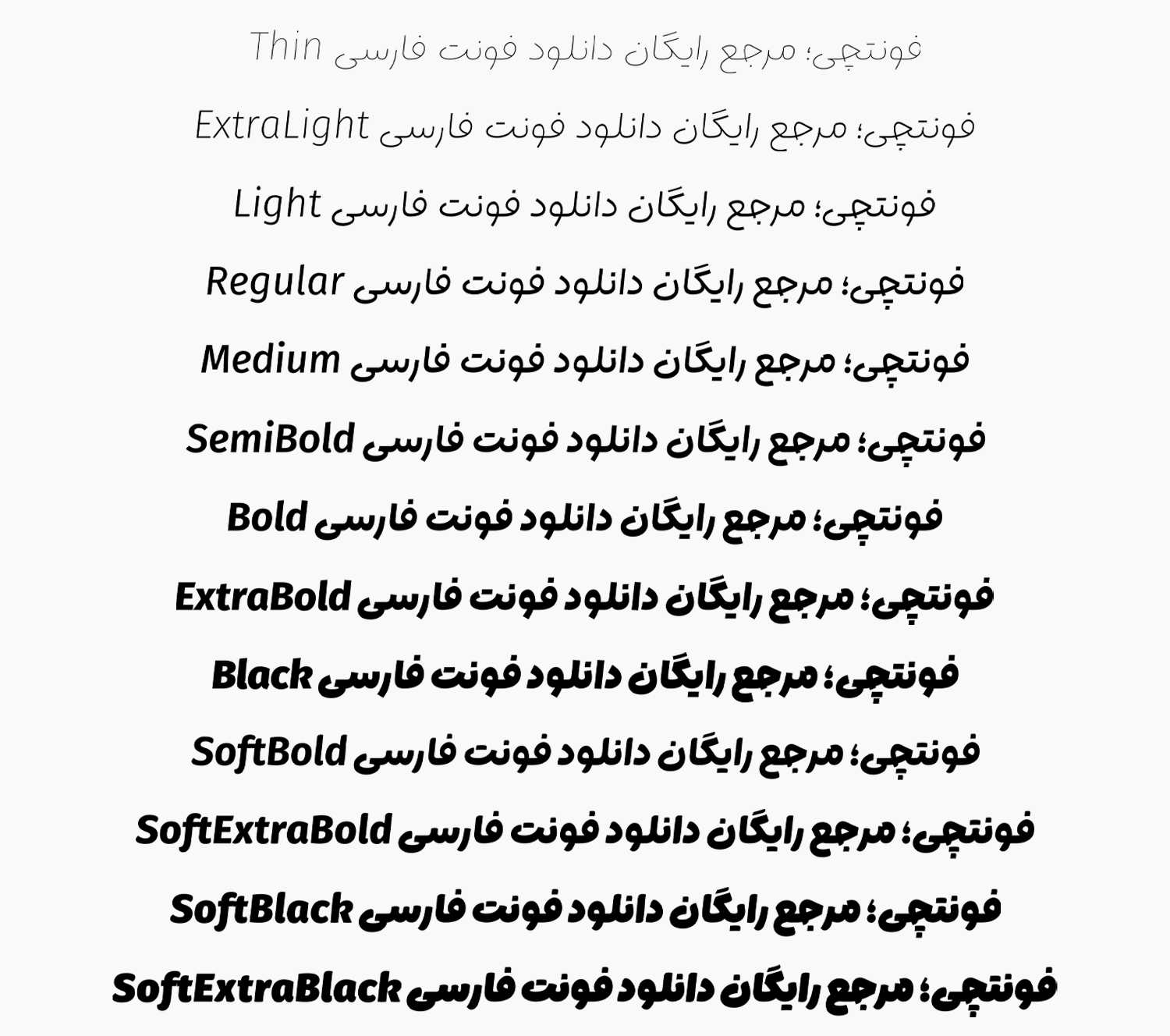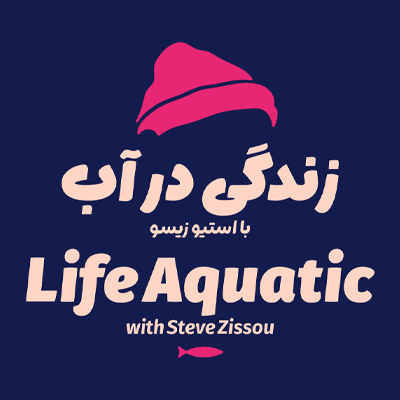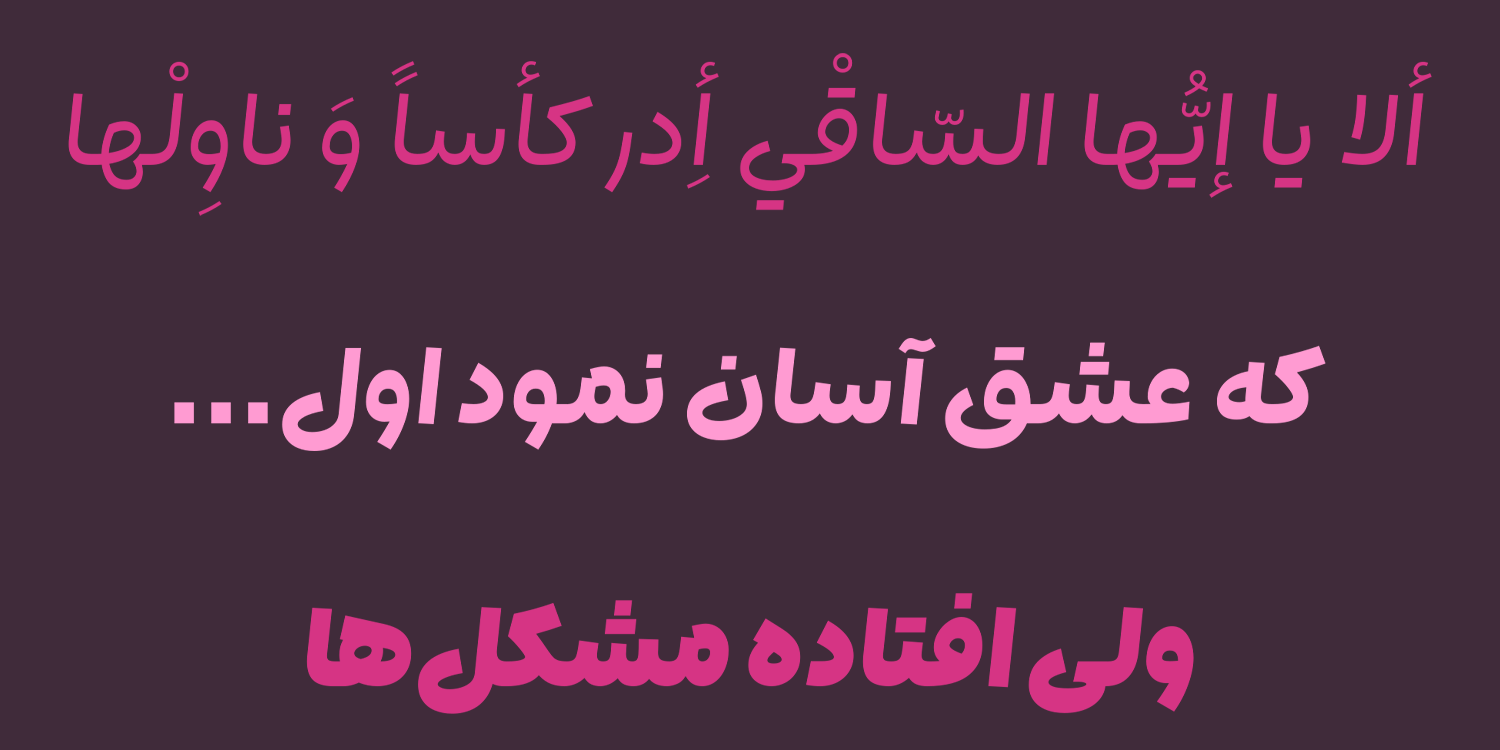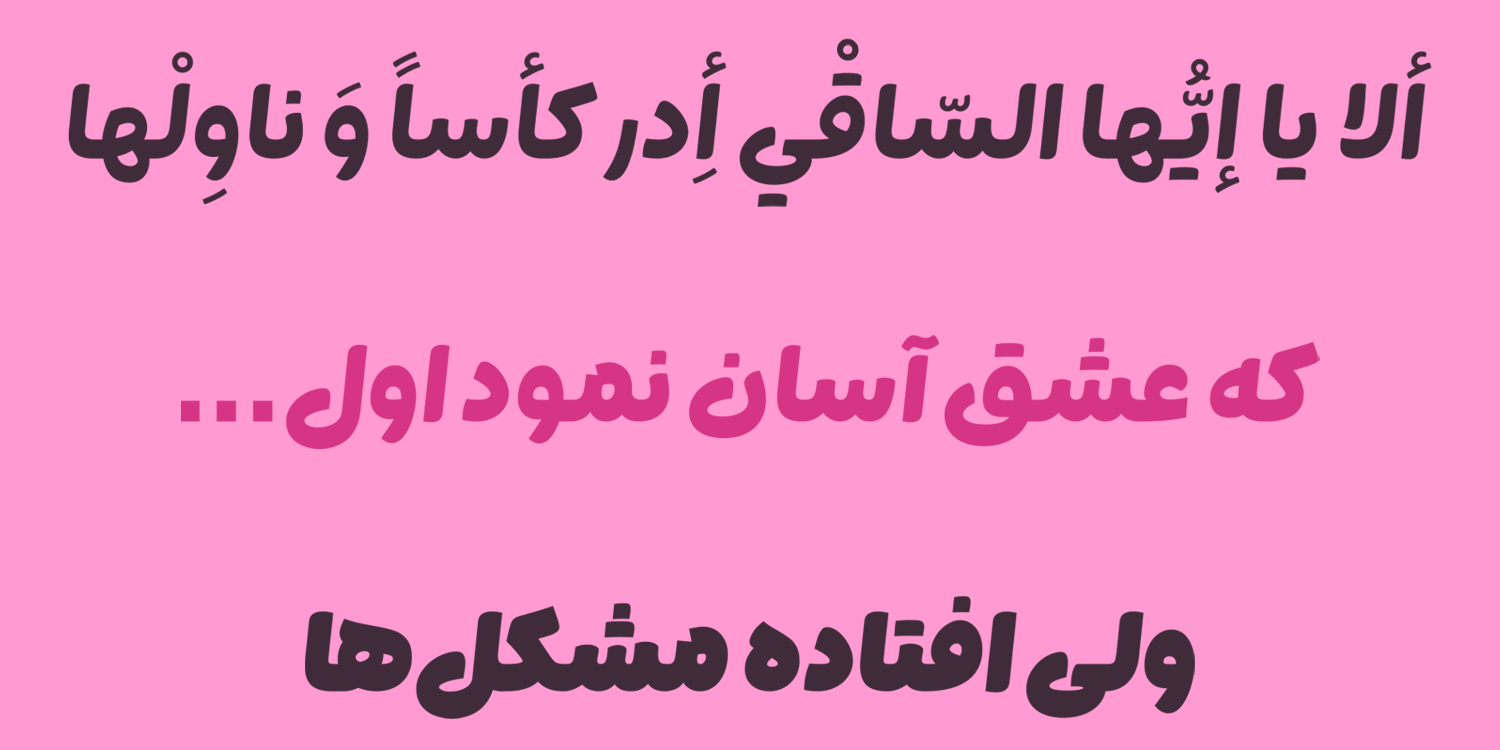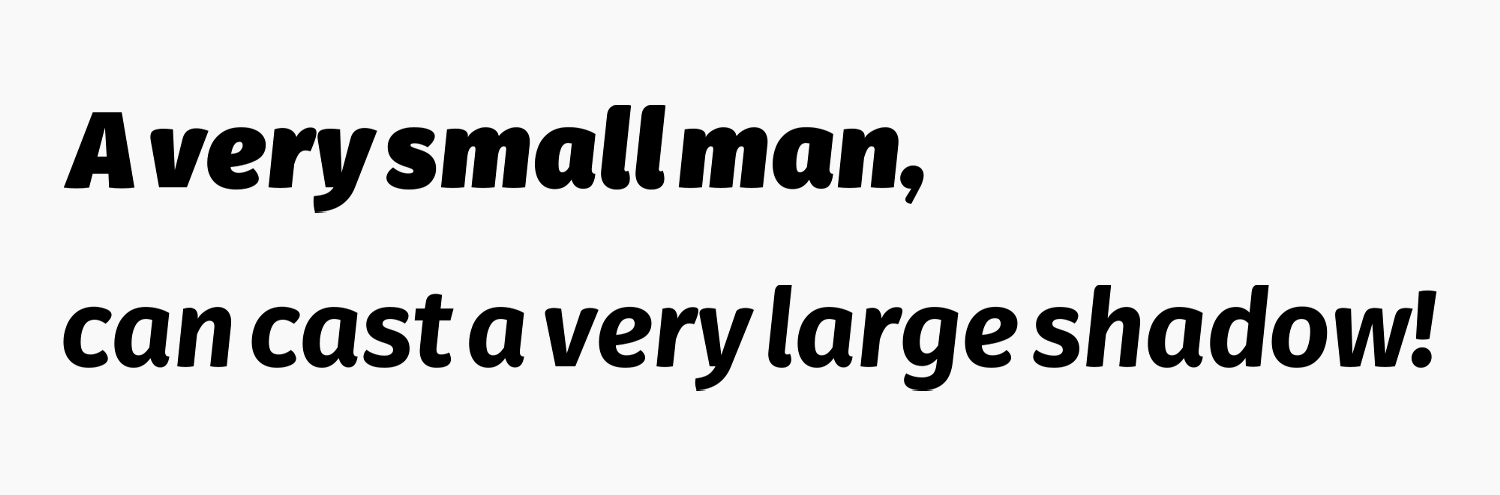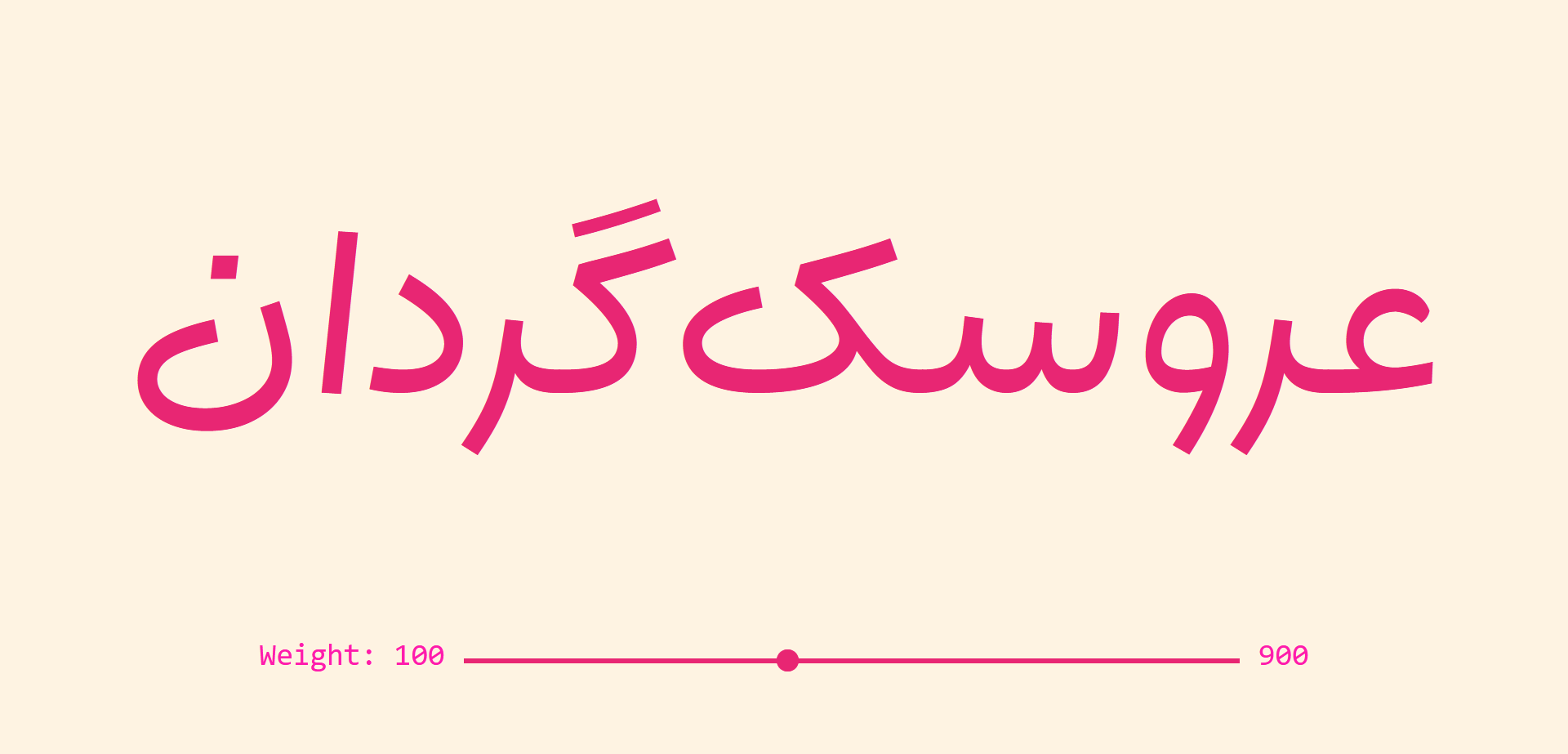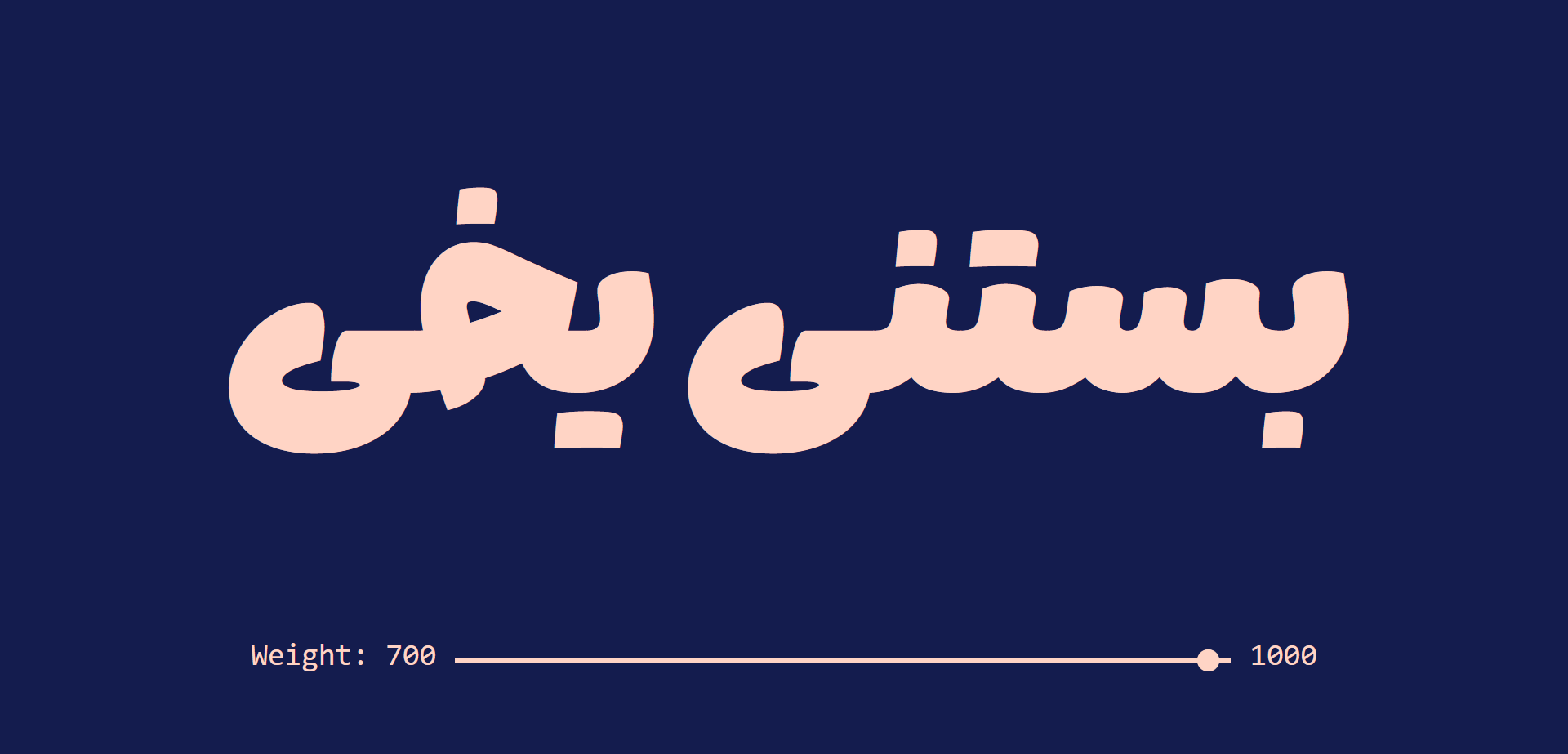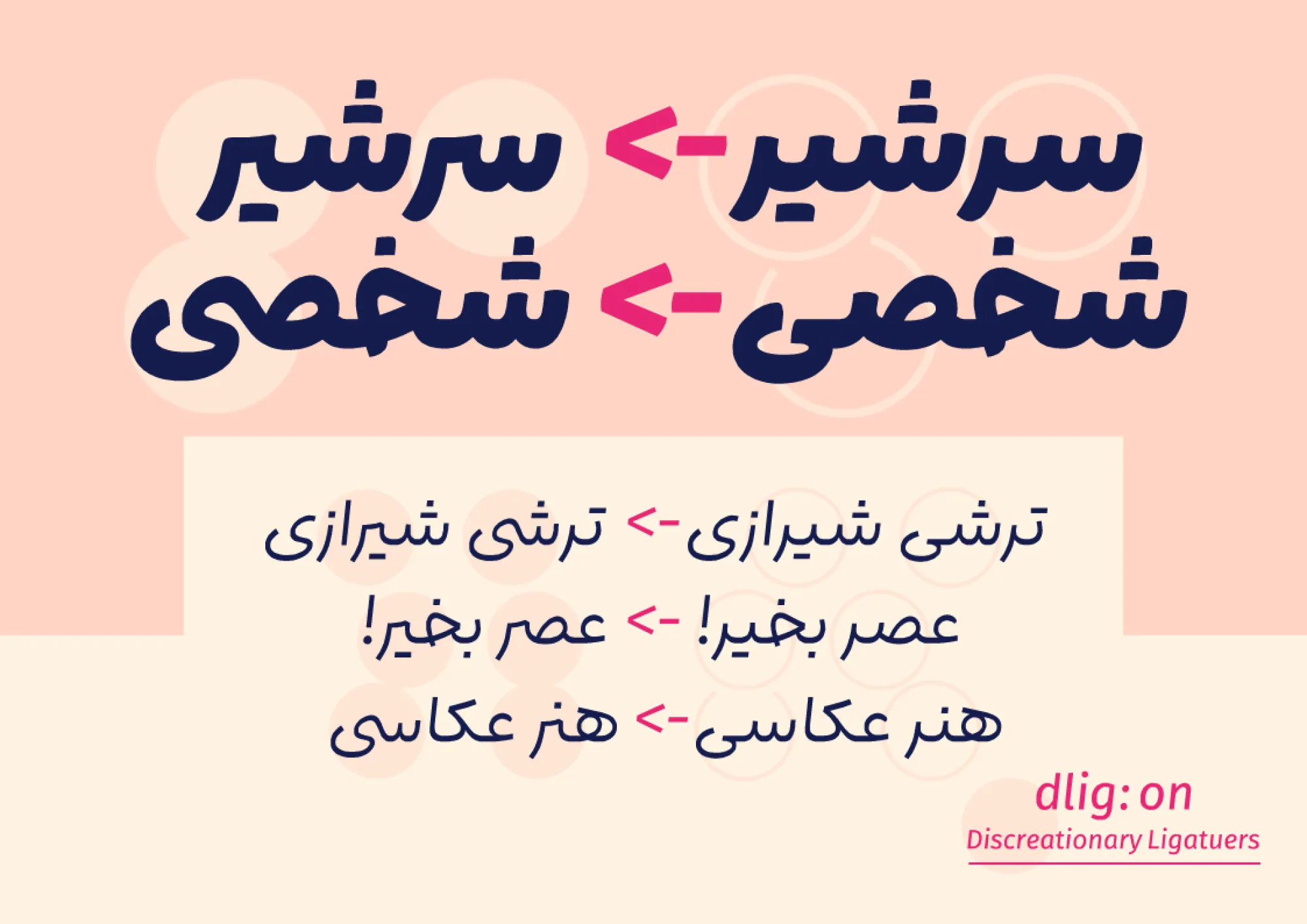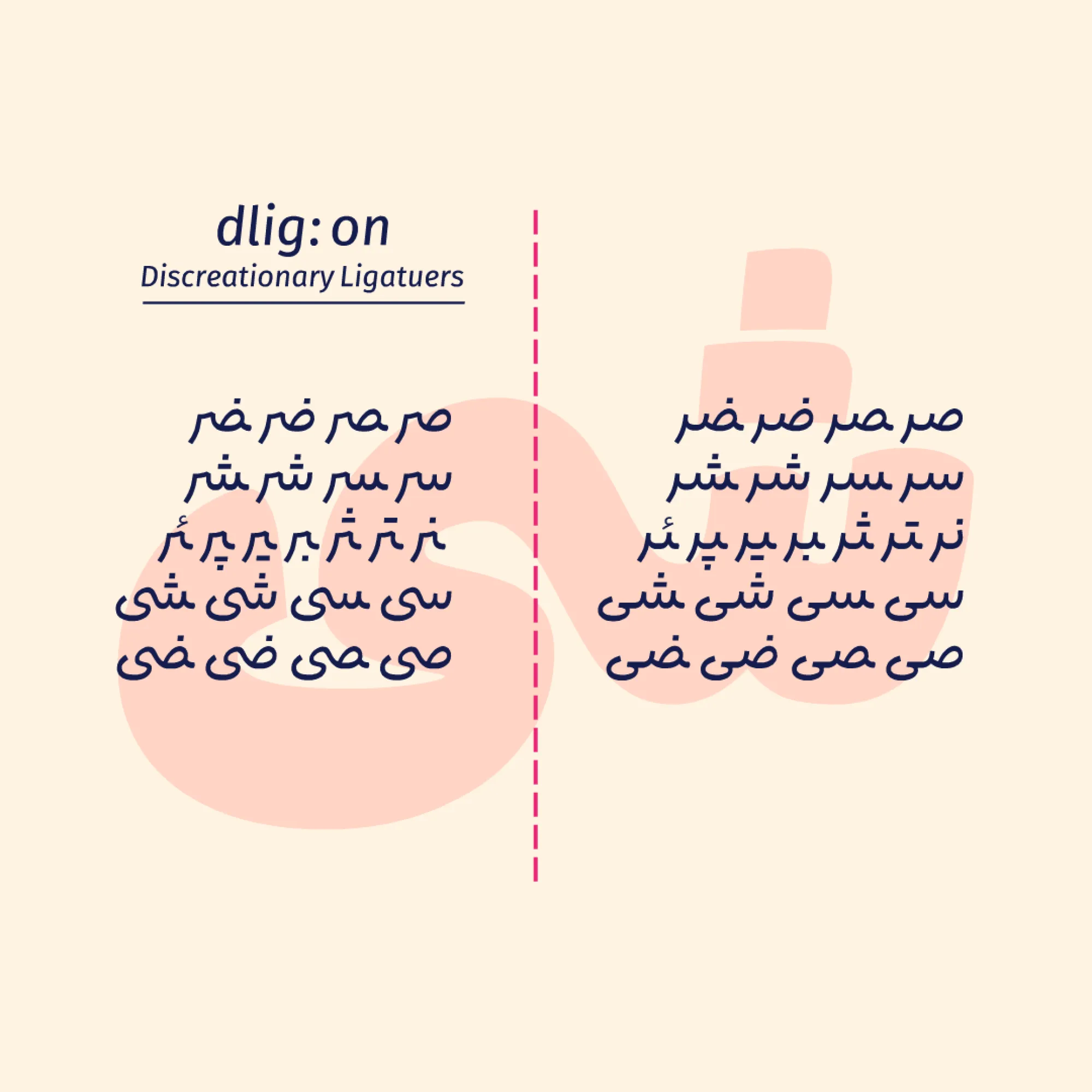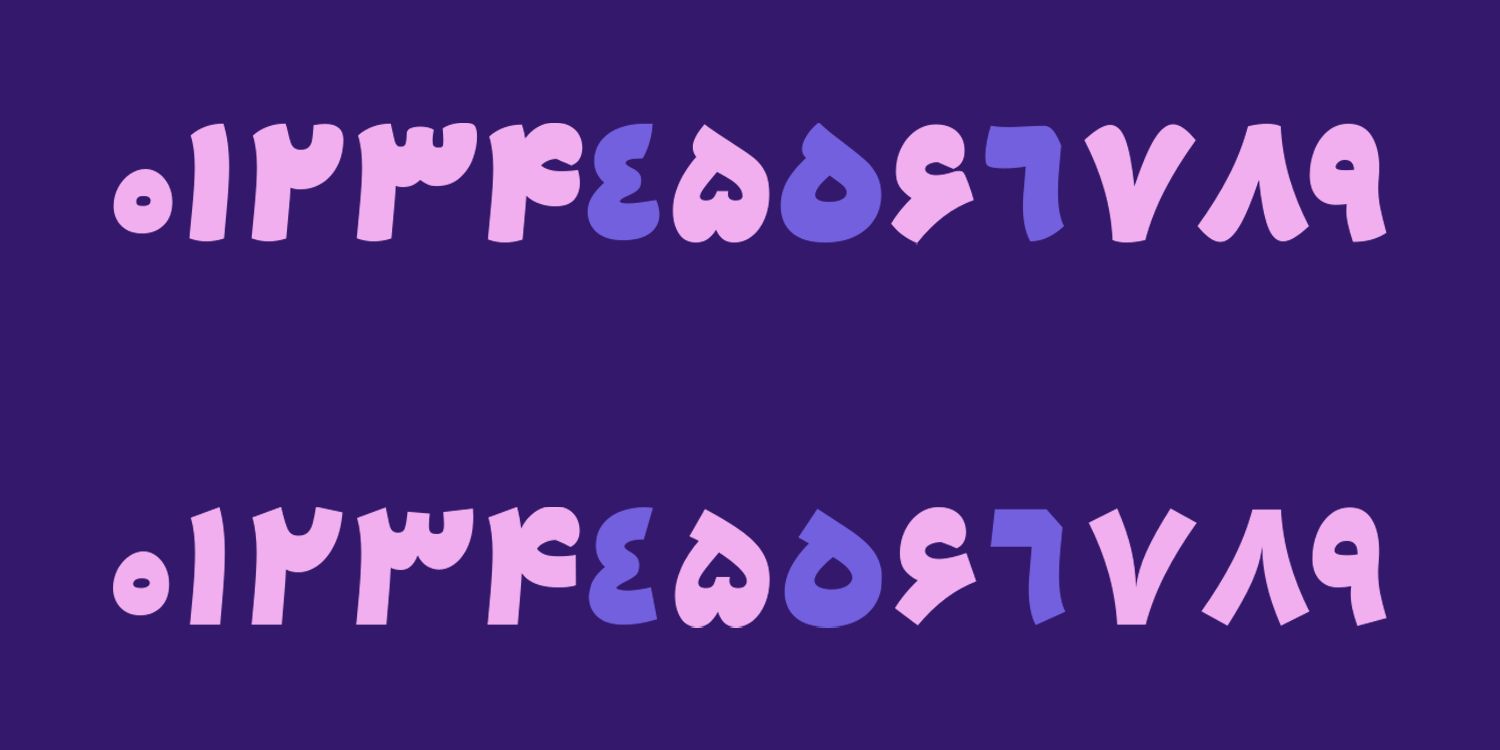
فونت لیانا (Liana)
فونت لیانا (به لاتین: Liana) در گروه فونتهای دست نویس قرار دارد که دارای ساختاری بسیار نرم و سنس خطی است که فرم حروف در این تایپفیس سیال بوده و دارای سبک نرمی هستند که این فونت را بیش از پیش دوستانه کرده است. فونت لیانا رایگان نبوده و شامل ۳ بسته مختلف است که در مجموع ۱۳ وزن مختلف را در چند سبک پشتیبانی میکند.
امین عابدی که از توسعه دهندگان و برترین طراحان فونت فارسی است این قلم را با ترکیبی از چند فونت استعداد، فرناز و مهر به این صورت ایجاد کرده است که در دو سبک طراحی شده و در مجموع با توجه به تنوع وزنی که دارد شامل ۹ وزن است ۴ وزن ضخیم دارای دو سبک هستند.
در ادامه این نوشته از سایت فونتچی به نقد و بررسی فونت لیانا خواهیم پرداخت؛ قلمی که دارای سبکی فانتزی دستنویس بوده و در عین حال با توجه به پشتیبانی از دو سبکی که دارد میتواند برای استفاده در عناوین، تبلیغات و فونت مناسب متن مناسب باشد.
بررسی و دانلود فونت لیانا (Liana)
فونت لیانا در دو سبک عادی سنس (Sans) و نرم (Soft) طراحی شده است. سبکهای سنس که شامل وزن ۱۰۰ تا ۹۰۰ را شامل میشوند مناسب برای استفاده در متنهای کوتاه تا بلند هستند که شامل ۹ وزن مختلف است.
در مقابل سبک سافت که دارای ظاهری نرمتر و دوستانهتر است، در ۴ وزن مختلف طراحی شده که شامل وزن ۷۰۰ تا ۱۰۰۰ است و میتوانید از این گروه فونت برای عناوین استفاده کنید که ظاهری نرمتر به متن شما خواهد داد.
سبک طراحی و وزن فونت لیانا
در طراحی فونت لیانا تمامی حروف و کاراکترها با زاویه ۶.۵ درجه طراحی شده که گذشته از ایتالیک کردن نسبی فونت، باعث شده تا قلم حس پویا و سرزندهای به خود بگیرد. سبک نقطه گذاری در این فونت تماما پیوسته است و نقاط در همه وزنها بدون نقطه جداگانه هستند.
نسخه سنس فونت لیانا برای استفاده در متنهای بلند و طولانی بهینه شده است که میتوانید برای استفاده در صفحات دیجیتال در وب گرفته تا اپلیکیشن موبایل از آن استفاده کنید. یا اینکه در صنعت چاپ از آن برای فونت کتاب بهره ببرید که عموما با توجه به ساختار دستنویس میتواند برای کتاب کودک و نوجوان، مجلات و کاتالوگ مناسب باشد.
در مقابل سبک سافت برای ساختارهای نمایشی بهینهسازی شده است که میتواند شامل استفاده در عناوین و تیترها باشد. از این سبک فونت نیز میتوانید در صفحات وب برای فونت عناوین و تیترها استفاده کنید. یا اینکه در صنعت چاپ از این سبکها برای جلد کتاب و مجلات بهره ببرید.
پشتیبانی از ۴ زبان مختلف
فونت لیانا از چهار زبان مختلف پشتیبانی میکند. گروه اول این زبانها بر اساس رسمخط فارسی هستند که شامل زبان فارسی، عربی و کوردی است. در هر سه این زبانها تمامی حروفی که دارای ساختار مشترک هستند برای هر زبان بر پایه گلیف استاندارد یونیکد طراحی شده است.
تمامی حروف در این زبانها دارای ساختار استانداردی هستند که با قرارگیری در کنار اعراب و کاراکترهای تزئینی موجب به هم ریختگی نمیگردد. متناسب با هر زبان میتوانید به اعراب اصلی، تنوینها، کاراکترهای تزئینی و کاراکترهای خاص همچون «تشدید، سکون، همزه» دسترسی داشته باشید.
همانطور که در تصویر بالا میبینید، این گروه از فونتها شامل نسخه سنس هستند که دارای ظاهری رسمی و در عین حال دست نویس هستند. میتوانید در این نسخه به وزنهای ۹ گانه نازک تا سیاه دسترسی داشته باشید و در متنهای کوتاه تا بلند از آن استفاده کنید.
در مقابل این سبک، سبک سافت (Soft) فونت لیارا قرار دارد که مشابه تصویر زیر بوده و شامل ۴ وزن ضخیم تا خیلی سیاه است. در این سبک فونت ساختار نرمتری دارد به طوریکه حروف و دندانهها ظاهری گرد، خمیده و دارای چشمیهای نرمتری هستند.
تمامی هر دو سبک برای زبانهای فارسی، عربی و کوردی از این ساختار پشتیبانی میکنند. طوری که برخی حروف مانند «ک، ی، ه، ؤ، ئ» در زبان عربی که متفاوت از نسخه فارسی هستند نیز گلیف استاندارد خود را دارند.
در فونت لیانا انگلیسی از طراحی اختصاصی بهره برده نشده است. برای زبانهای لاتین این فونت از قلم اپنسورس Fira Sans Italic استفاده شده که کمی در ان دخل و تصرف ایجاد شده تا با نسخه فارسی هماهنگتر باشد. خصوصا در نسخه سافت که دارای ظاهری نرمتر است.
فونت لیانا وریبل با متغیر وزن
قابلیت دیگر فونت لیانا وریبل بودن آن است. در این قلم برای هر دو سبک فونت دسترسی به نسخه مخصوص متغیر را دارید که امکان دسترسی به تمامی وزنهای فونت را در هر دو سبک در اختیارتان قرار خواهد داد.
نسخه وریبل فونت لیانا از یک متغیر وزن با نام Weight پشتیبانی میکند که به شما امکان تغییر وزن فونت را متناسب با وزنهایی که در هر دو سبک وجود دارد خواهد داد. میتوانید در صفحات وب با استفاده از متغیر وریبل وزن دلخواه را استفاده کرده یا اینکه در نرمافزارهای گرافیکی مثل فتوشاپ از تنظیمات Open Type وزن فونت را تغییر دهید.
نسخه وریبل سنس که در تصویر بالا نمونه آن را میبینید شامل وزن ۱۰۰ تا ۹۰۰ است که میتوانید از تمام وزنهای ۹ گانه نازک تا سیاه را استفاده کنید.
نسخه وریبل سبک سافت نیز شامل وزنهای ۴ گانه مشابه تصویر بالا است که بین وزن ۷۰۰ تا ۱۰۰۰ که شامل وزن ضخیم تا خیلی سیاه است را شامل میشود.